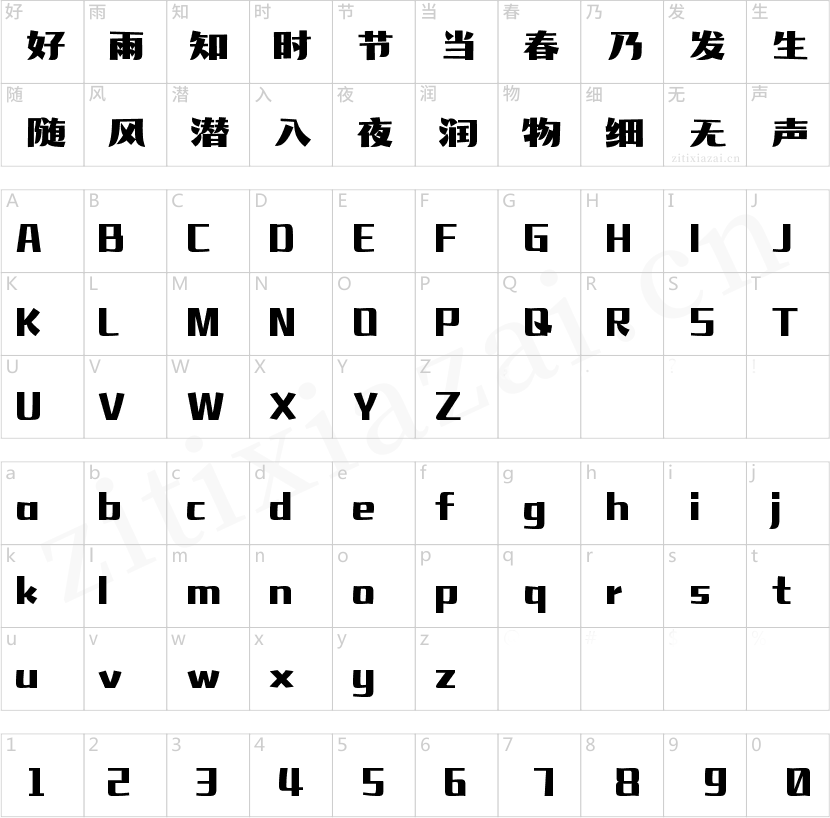
字魂麻辣体
字魂麻辣体,这款字体结构工整、笔画清晰,兼顾美观与易读性,适用于标题、正文、海报、包装、LOGO 等多种场景。字形优雅稳定,风格百搭耐看,适配日常排版与创意设计,让文字呈现更舒适、更具质感。字魂麻辣体一笔一画,皆是细节,以均衡的比例、流畅的线条打造舒适视觉体验,字形端正大气,风格简约现代。无论是商业设计、品牌宣传还是日常排版,都能轻松驾驭,让文字更有格调与力量。字魂麻辣体字体下载。
字魂字体字魂麻辣体字体是由字魂创意字库设计并生产的一款可商用的字体,被收录于字魂先锋系列。该字体支持GB-2312标准以及最新的字魂ZH7144标准,包含7144个中文、字母、符号和数字,字体类型偏向黑体,具有时尚的风格,在市面上广泛用于餐饮食品、排版阅读、房地产等场景。